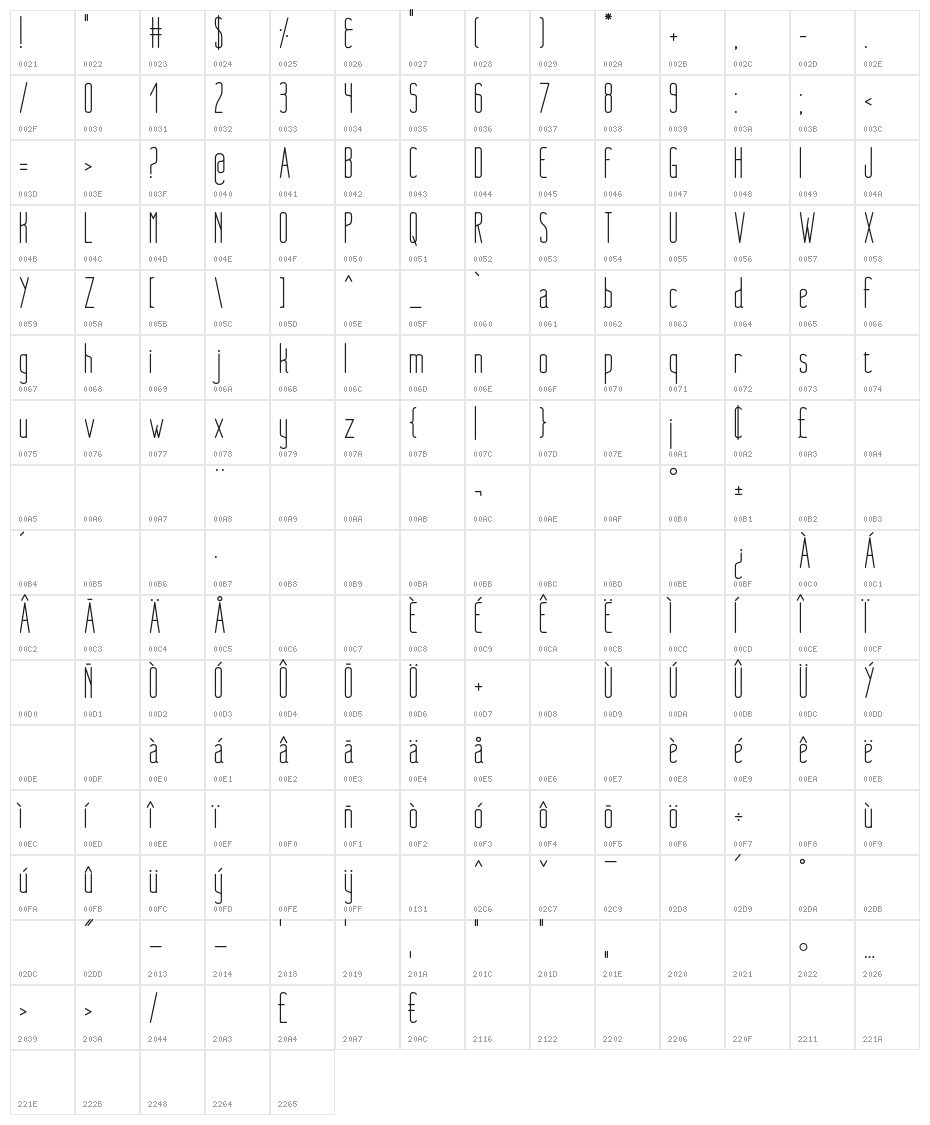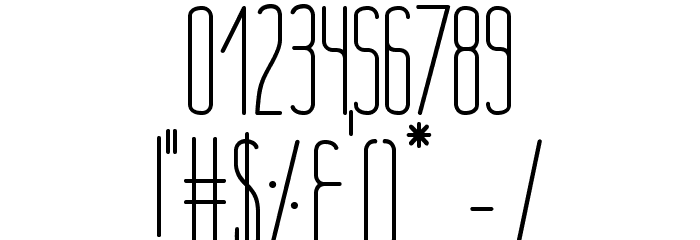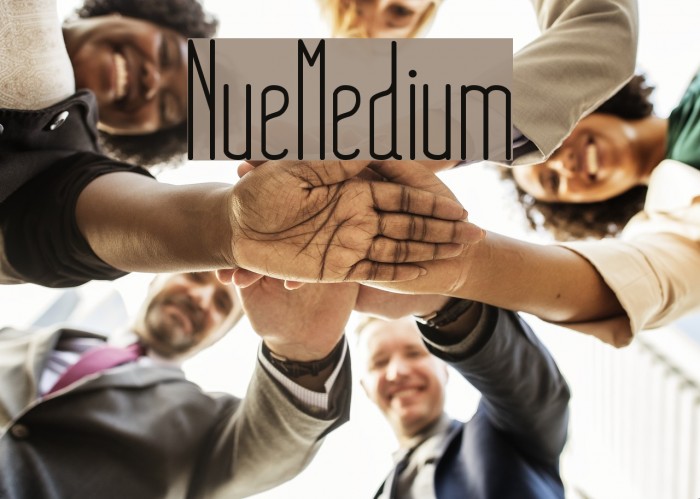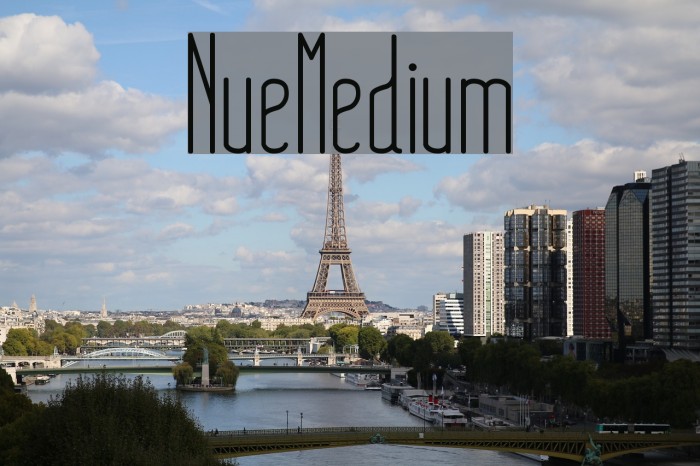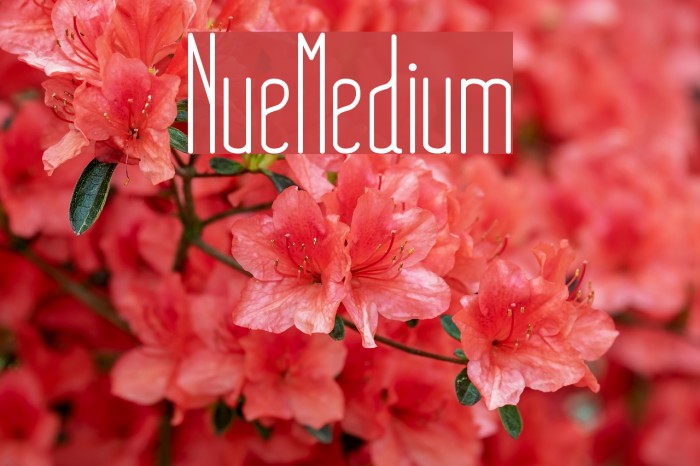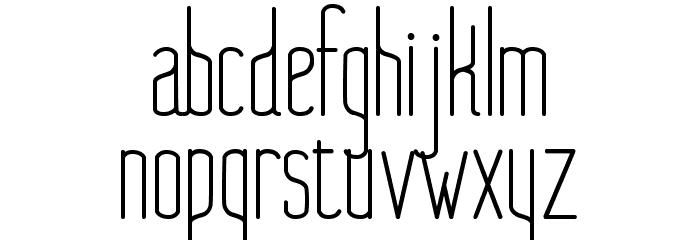
NueMedium Font
| Caz de utilizare | Headlines, Logos, Digital interfaces |
| Proiecte propuse | Ideal for branding, editorial design, posters, and digital interfaces where a modern and sleek aesthetic is desired. |